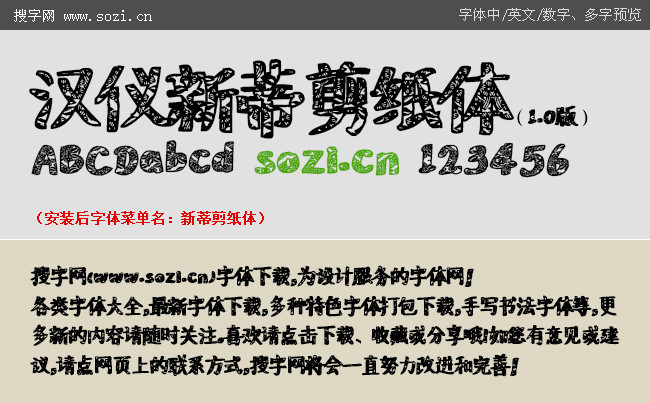
漢儀新蒂剪紙?bào)w1.0
搜字網(wǎng)給大家提供一款漢儀新蒂剪紙?bào)w1.0中文字體下載。漢儀新蒂剪紙?bào)w是一款卡通POP字體,由漢儀新蒂工作室出品,漢儀新蒂工作室成立于2016年,由漢儀字庫(kù)與新蒂字體聯(lián)合成立字體富有變化,字形充滿童趣,適合兒童產(chǎn)品畫(huà)冊(cè)、兒童產(chǎn)品包裝設(shè)計(jì)、海報(bào)設(shè)計(jì)、網(wǎng)頁(yè)標(biāo)題設(shè)計(jì)等應(yīng)用。(本字體為個(gè)人非商用版,如需要商用請(qǐng)聯(lián)系漢儀公司購(gòu)買版權(quán))